Handmade letters everywhere
En este blog hemos hablado de lettering (sea cual sea la técnica) para comercios, como podrían ser los casos de las entradas de Dana Tanamachi o Chris YoonPues bien, este articulo viene porque en cuestión de poco tiempo he visto varios trabajos de este estilo allí por donde he estado ¿será que ahora me fijo más? ¿será que me estoy volviendo loco con las letras? seguramente sean ambas pero la cuestión es que me dije voy hacer un articulo en Lettering Time donde recoja trabajos de lettering hechos a mano en tiendas, restaurantes, cafeterías y demás.
Empiezo por el principio, mostrando algunos de los que he visto en persona en estos últimos días ( disculpar por la calidad de las imágenes, están tomadas con el móvil):
-Por las calles de Valencia me encontré con algunos trabajos del calígrafo y amigo de Lettering time Giuseppe Salerno:
- Mas tarde, hace apenas unos dias, de vuelta a casa por Barcelona (donde he pasado una temporada) me encontré con el Restaurante Piscolabis:
-Ese mismo día, y la misma acera hacia adelante, llegue al centro comercial L'illa diagonal, donde me encontré con Lush (tienda de cosmética fresca hecha a mano):
Aunque este último ejemplo no sean exactamente lettering hechos a mano y mas bien tipografías que lo simulan, el efecto buscado es el mismo ( pero un servidor siempre preferirá lo hecho a mano).
Pues bien, una vez contados estos descubrimientos os dejo una mini galería de trabajos de este tipo que he encontrado por la red:
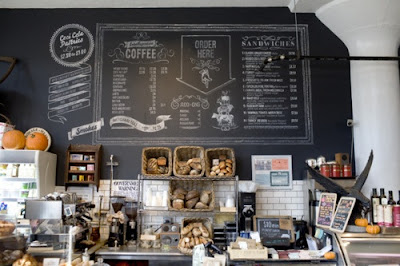
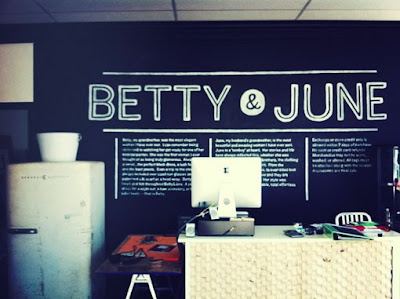
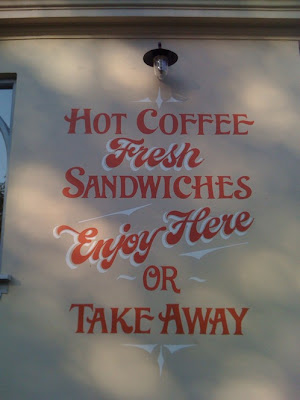
Y vosotros que creéis ¿es una moda pasajera? ¿es algo que siempre se ha hecho para referirnos a comercios donde lo que ofrecen tiene un valor artesanal? ¿se seguirá haciendo en un futuro?